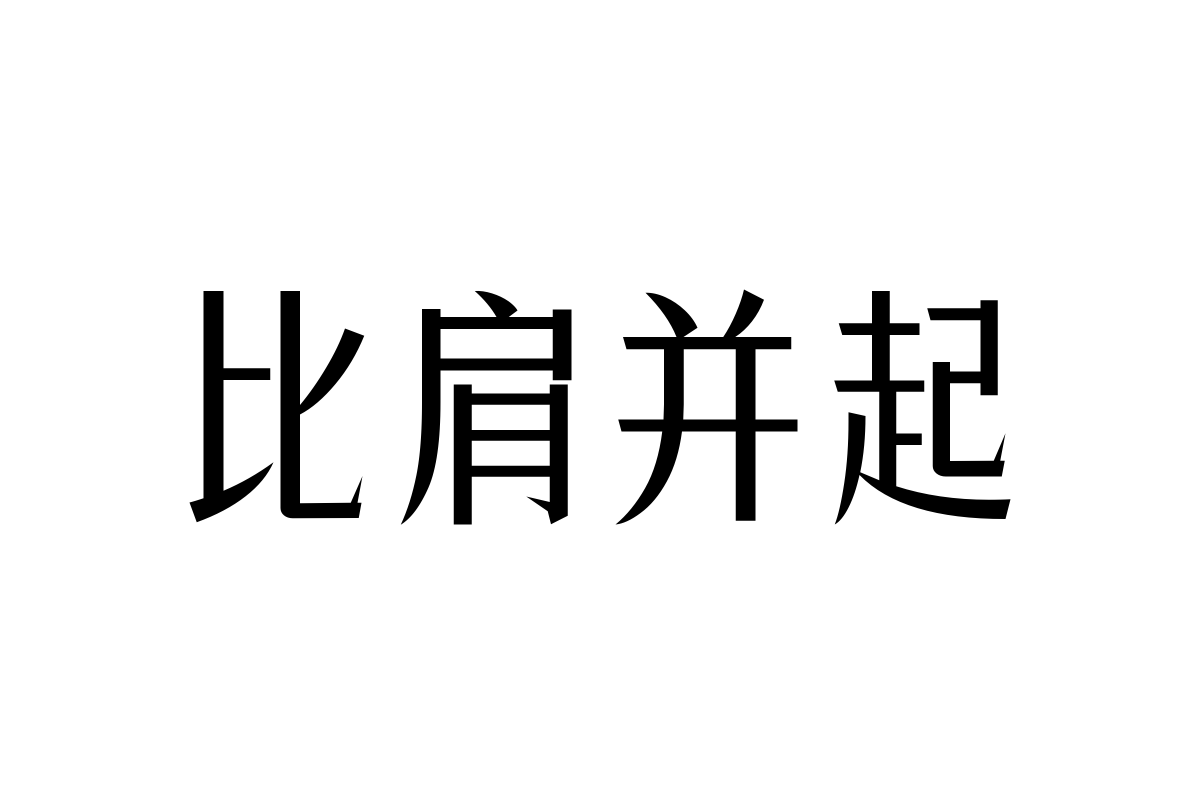
三极锐宋黑简体字体是一款由上海三极锐科技有限公司开发的中文简体字库,主要用于设计、出版、印刷等领域。这款字体的特点是字形简洁明了,笔画流畅,易于阅读和书写。同时,它的设计风格现代时尚,符合现代人的审美需求。
三极锐宋黑简体字体的字形特点是:笔画粗细适中,结构紧凑,线条清晰,易于辨认。它的字形特点使得它在设计中具有较高的辨识度,能够有效地提高信息的传递效率。
此外,三极锐宋黑简体字体还具有良好的可读性,无论是在哪种字体大小下,都能保持清晰的视觉效果。这使得它在印刷、电子屏幕上显示等方面具有广泛的应用前景。
总的来说,三极锐宋黑简体字体是一款实用性强、适应性广的中文简体字库,适用于各种设计、出版、印刷等领域。